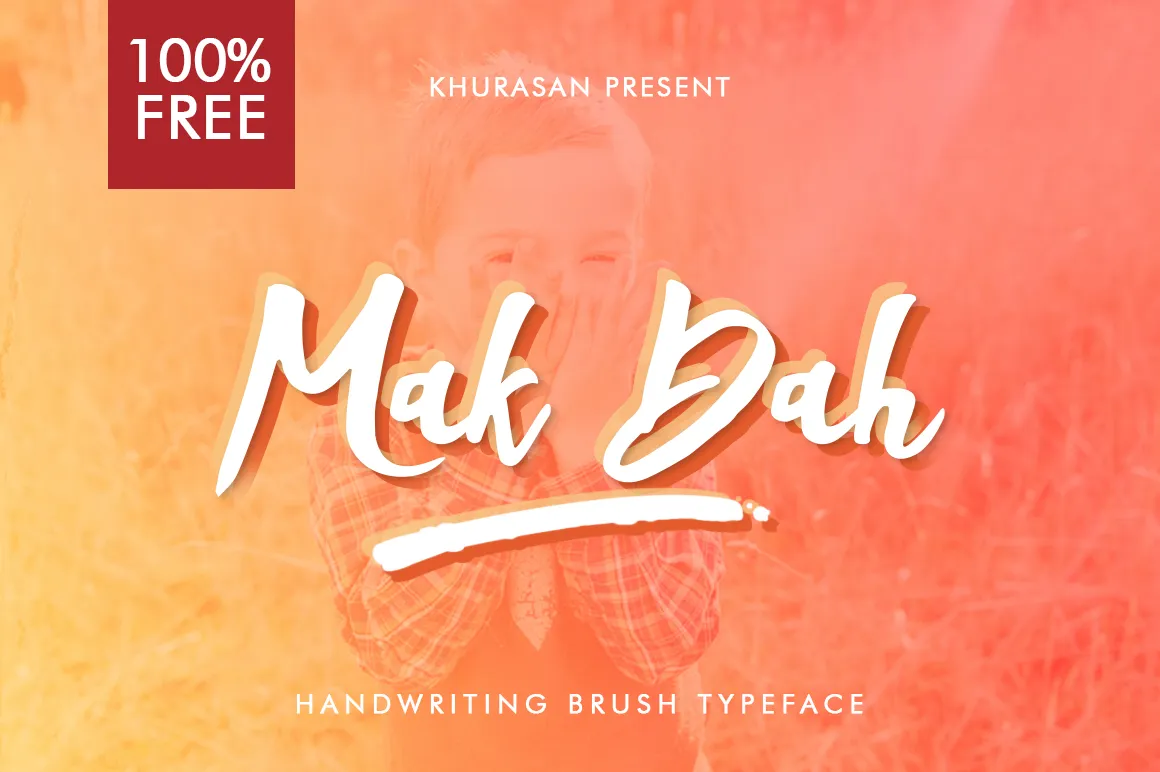
Mak Dah Brush Font
A Mak Dah Brush Font é uma fonte exclusiva criada pelo designer Hamilton, misturando influências da tipografia de xilográfica com um tom serpenteante e fluido na base da letra. Esta fonte casual e elegante pode ser usada tanto para gráficos pessoais quanto em materiais publicitários, oferecendo uma liberdade impressionante para expressar sua identidade visual. Perfeita tanto para marcas como cartões de visita, embalagens, fliers, logotipos, fotografias e até mesmo livros e panfletos, a Mak Dah Brush Font é um recurso indispensável para qualquer designer gráfico que deseja adicionar uma dose única e distintiva ao seu trabalho.